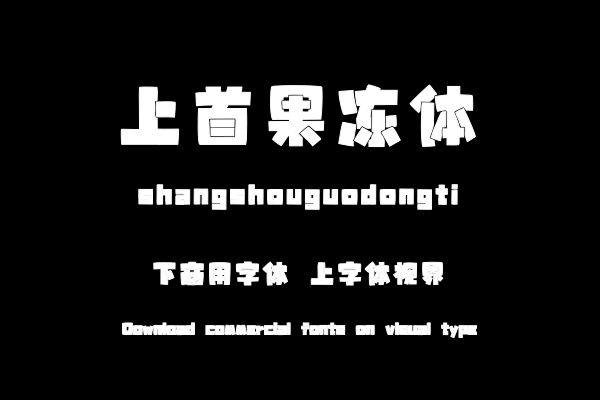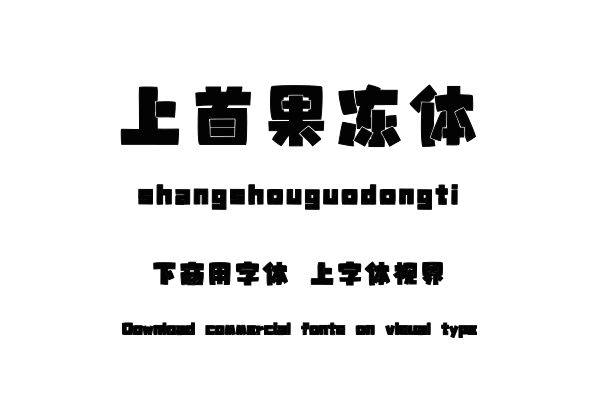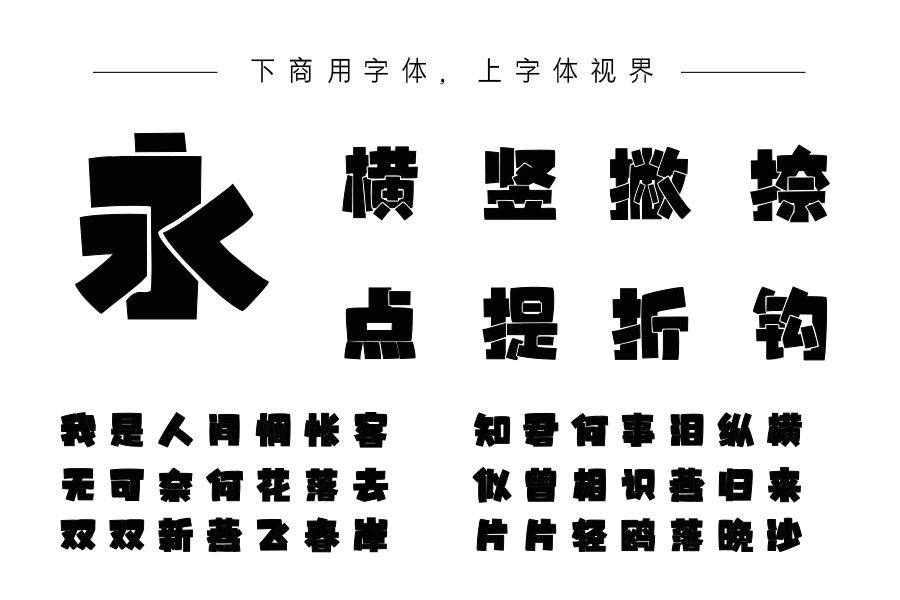
上首果冻体,简体中文约6763字,字体笔画横不平,竖不直,但正是因为这种不循规蹈矩,打破常规的做法,让字体显得调皮可爱,古灵精怪,像小孩子手中Q弹的果冻,在阳光......购买须知:“下载服务费”与“字体VIP”所获得字体 仅用于个人非商用, 商用请联系付费授权。本字体为电脑用字,手机没有root权限不支持直接手机换字(手机如何root,请自行百度搜索教程)。购买前请先 了解清楚后再付款 ,字体为虚拟产品无法回收 一旦购买不支持退款。